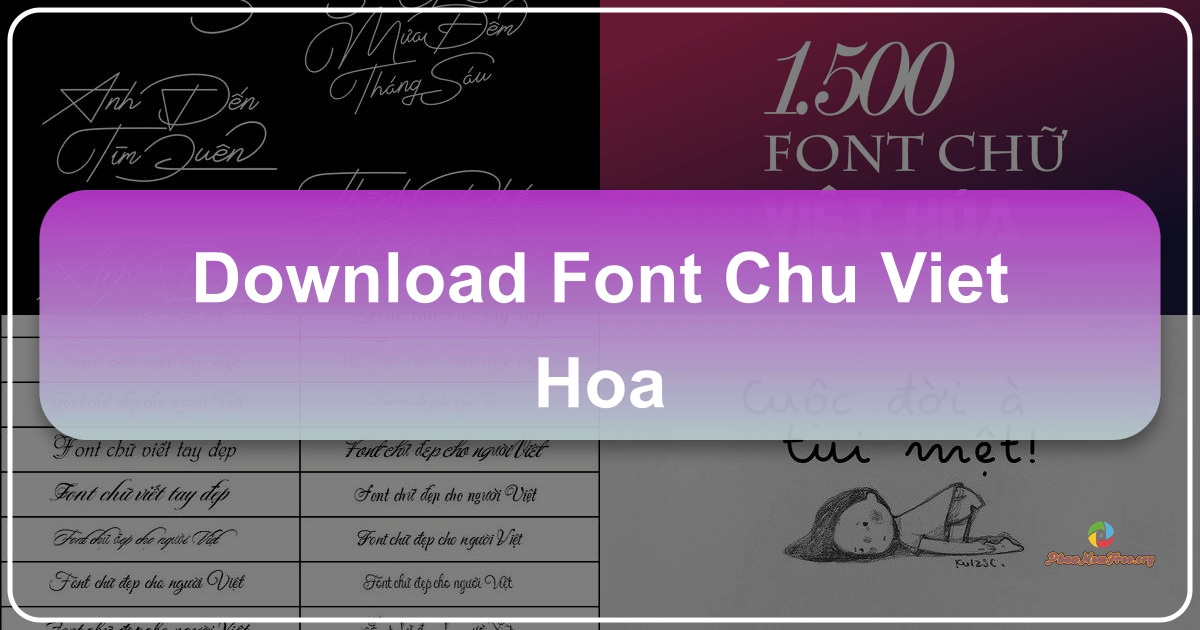
Thiết kế đồ họa đòi hỏi sự tinh tế và sáng tạo, không chỉ ở bố cục, màu sắc mà còn ở sự lựa chọn phông chữ. Một phông chữ phù hợp có thể nâng tầm thiết kế, tạo nên điểm nhấn và truyền tải thông điệp hiệu quả hơn. Hiểu được điều này, bộ sưu tập 500 Font chữ Việt hóa dành riêng cho Photoshop ra đời, mang đến cho các nhà thiết kế một kho tàng phong phú, đa dạng các kiểu chữ, giúp họ thỏa sức sáng tạo và tạo nên những tác phẩm ấn tượng.
Sự Cần Thiết Của Font Chữ Việt Hóa Trong Thiết Kế
Đối với những người dùng chỉ cần soạn thảo văn bản đơn giản, trò chuyện hay gửi email, các bộ font chữ phổ biến như UTM, Unicode hay VNI đã đáp ứng đủ nhu cầu. Tuy nhiên, đối với các nhà thiết kế đồ họa, yêu cầu về phông chữ lại cao hơn nhiều. Họ cần những kiểu chữ độc đáo, tinh tế, thể hiện được cá tính riêng của tác phẩm, tạo nên sự khác biệt và thu hút người xem.
Bộ font chữ thông thường thường thiếu sự đa dạng về kiểu dáng, phong cách, dẫn đến sự trùng lặp và thiếu tính sáng tạo trong thiết kế. Việc sử dụng các font chữ quốc tế chưa được Việt hóa cũng gây khó khăn trong việc hiển thị tiếng Việt chính xác, dẫn đến lỗi font, chữ bị lỗi font, thiếu dấu hoặc hiển thị sai khiến cho sản phẩm mất đi tính thẩm mỹ. Vì vậy, một bộ font chữ Việt hóa chất lượng cao là điều vô cùng cần thiết cho các nhà thiết kế đồ họa chuyên nghiệp cũng như những người yêu thích thiết kế.
500 Font Chữ: Một Kho Tàng Vô Cùng Phong Phú
Bộ 500 Font chữ Việt hóa này chính là giải pháp hoàn hảo cho vấn đề trên. Với số lượng lên đến 500 font chữ, bộ sưu tập này cung cấp một kho tàng phong phú các kiểu chữ, đáp ứng mọi nhu cầu thiết kế, từ đơn giản đến phức tạp, từ cổ điển đến hiện đại. Mỗi font chữ đều được thiết kế với kiểu dáng, hoa văn uốn lượn khác nhau, mang đến sự đa dạng và độc đáo cho các sản phẩm thiết kế.
Tính Năng Nổi Bật Của Bộ Font Chữ:
- Số lượng phong phú: 500 font chữ Việt hóa, đảm bảo đáp ứng mọi nhu cầu thiết kế.
- Chất lượng cao: Các font chữ được Việt hóa kỹ lưỡng, đảm bảo hiển thị tiếng Việt chính xác và sắc nét.
- Đa dạng phong cách: Từ font chữ thanh lịch, sang trọng đến font chữ năng động, hiện đại, bộ sưu tập đáp ứng mọi phong cách thiết kế.
Ứng Dụng Trong Thiết Kế
Bộ 500 Font chữ Việt hóa không chỉ hữu ích cho các nhà thiết kế chuyên nghiệp mà còn phù hợp với cả những người mới bắt đầu làm quen với thiết kế đồ họa. Việc sở hữu một bộ font chữ đa dạng sẽ giúp người dùng:
- Tăng tính sáng tạo: Khám phá và thử nghiệm nhiều kiểu chữ khác nhau, tạo ra các thiết kế độc đáo và ấn tượng.
- Nâng cao chất lượng thiết kế: Chọn font chữ phù hợp với từng dự án, giúp truyền tải thông điệp một cách hiệu quả.
- Tiết kiệm thời gian: Không cần mất thời gian tìm kiếm các font chữ trên mạng, giúp rút ngắn thời gian hoàn thành dự án.
- Thỏa mãn đam mê: Khám phá thế giới font chữ đa dạng và phong phú, thỏa mãn niềm đam mê thiết kế.
So Sánh Với Các Bộ Font Khác
So với các bộ font chữ khác, bộ 500 Font chữ Việt hóa này nổi bật hơn nhờ số lượng font chữ phong phú, chất lượng cao và được Việt hóa kỹ lưỡng. Điều này giúp người dùng tránh được các lỗi font, đảm bảo tính thẩm mỹ và chuyên nghiệp cho các sản phẩm thiết kế. Hơn nữa, việc cung cấp miễn phí bộ font chữ này giúp người dùng tiết kiệm chi phí đáng kể so với việc phải mua từng font chữ riêng lẻ.
Kết Luận
Bộ 500 Font chữ Việt hóa cho Photoshop là một công cụ thiết kế không thể thiếu đối với các nhà thiết kế đồ họa. Với số lượng font chữ đa dạng, chất lượng cao và dễ dàng sử dụng, bộ font chữ này giúp người dùng thỏa sức sáng tạo, tạo ra những sản phẩm thiết kế ấn tượng và chuyên nghiệp. Hãy tải xuống và trải nghiệm ngay bộ font chữ tuyệt vời này để nâng tầm thiết kế của bạn lên một tầm cao mới. Đây chắc chắn là một lựa chọn lý tưởng cho mọi nhà thiết kế, từ người mới bắt đầu cho đến những chuyên gia giàu kinh nghiệm. Việc sở hữu một bộ font chữ đa dạng và chất lượng sẽ là bước đệm quan trọng giúp bạn tạo nên những tác phẩm thiết kế độc đáo và thành công.